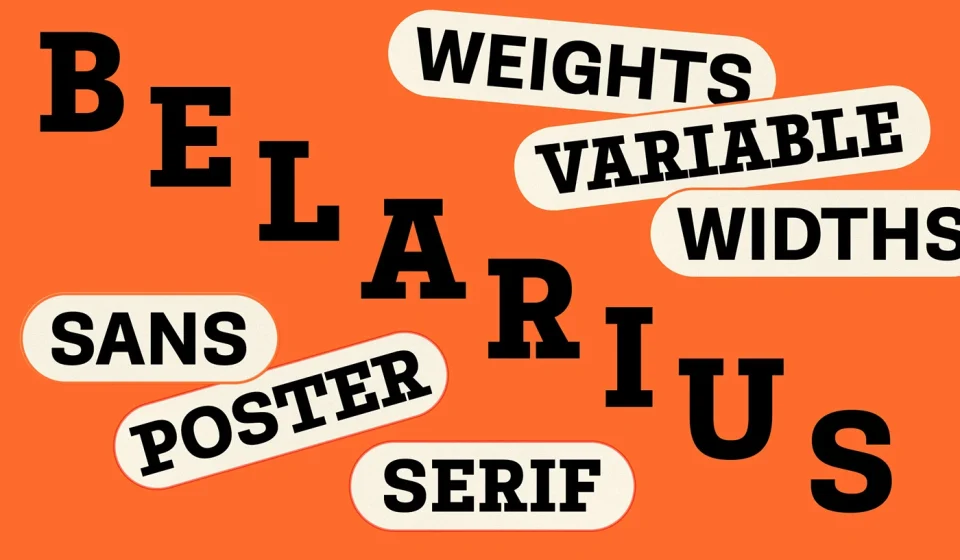
فونت Belarius؛ پادشاه تایپوگرافی، پوستر و بستهبندی!
اگه دنبال یک تایپفیس فوقالعاده مدرن، لوکس و همهفنحریف برای پروژههای گرافیکی، برندینگ یا پوسترهای تبلیغاتی میگردی، فونت Belarius یک شاهکار بینظیره. این فونت برنده جایزه معتبر Clap Platinum 2021 برای بهترین فونت تیتر شده و با ترکیب استایلهای Sans، Serif و Poster، دست طراح رو برای خلق تایپوگرافیهای جذاب کاملاً باز میذاره.
ویژگیها و امکانات برجسته فونت انگلیسی Belarius
این مجموعه فقط یک فونت معمولی نیست، بلکه یک سیستم تایپوگرافی کامل با کنترل ۳ محوره متغیره که میتونی بینهایت ترکیب ازش استخراج کنی:
- تنوع بینظیر استایلها: دارای ۹۰ استایل مختلف به همراه ۲ فونت متغیر (Variable Fonts) برای دسترسی به بینهایت حالت وزنی و ضخامتی.
- کنترل ۳ محوره متغیر (3-Axis Variable): قابلیت تغییر نرم و اسلایدری از حالت Sans به Slab Serif، و از عرضهای باریک (Condensed) به پهن (Expanded).
- طراحی شده برای عناوین و برندینگ: بهترین گزینه برای طراحی لوگوتایپ، عناوین مجلات، پوسترهای رویداد، بستهبندی محصولات لوکس و تبلیغات محیطی.
- برنده جایزه بینالمللی: دارنده مدال پلاتینوم Clap 2021 بهعنوان برترین فونت برای تیترها و عناوین اصلی.
منظور از فونت متغیر (Variable Font) در تایپفیس Belarius (بلاریوس) چیست؟
فونت متغیر یا Variable Font در تایپفیس Belarius (بلاریوس) به شما اجازه میدهد تنها با ۲ فایل فونت اصلی، ضخامت (Weight)، عرض (Width) و استایل فونت (از Sans تا Slab Serif) را بهصورت کاملاً اسلایدری و بینهایت حالت مختلف تغییر دهید و دقیقاً به استایل دلخواهتان برسید.
آیا فونت انگلیسی Belarius (بلاریوس) برای طراحیهای تجاری مثل بستهبندی و لوگوتایپ مناسب است؟
بله کاملاً! فونت انگلیسی Belarius (بلاریوس) برنده جایزه Clap Platinum شده و دقیقاً برای استفاده در عناوین اصلی (Headlines)، پوسترهای تبلیغاتی، طراحی بستهبندی محصولات، برندینگ و لوگوتایپهای مدرن طراحی شده است.